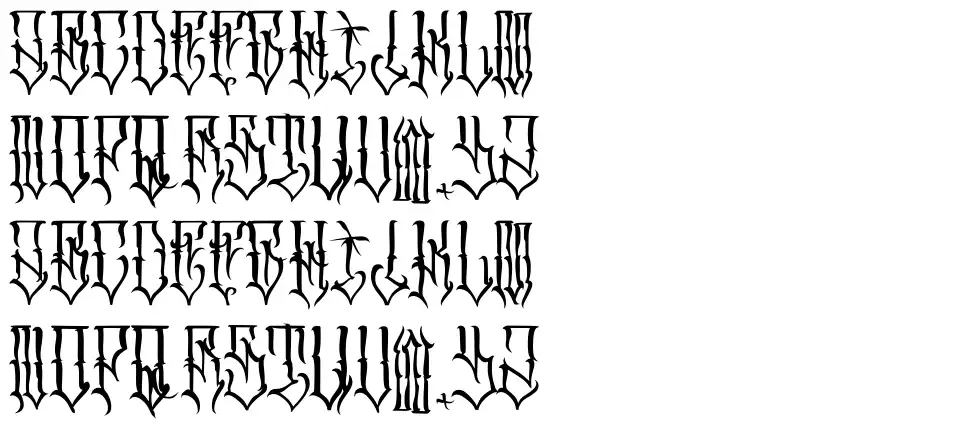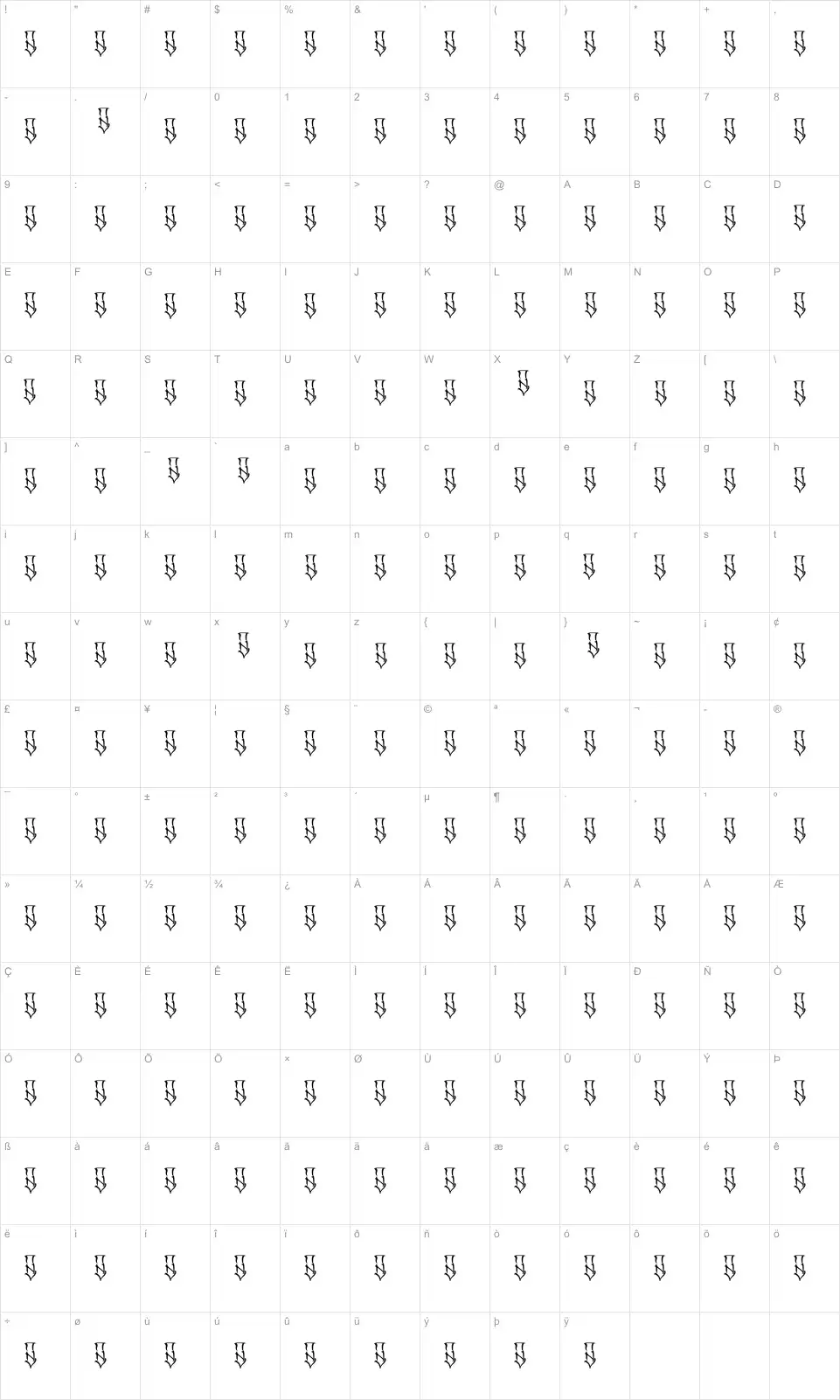
SR Cuen Font – Download Grátis
A fonte SR Cuen Font, criada pelo designer Cuen Medina, é uma escolha perfeita para aqueles que procuram um estilo de letra desenhado em graffiti. Suas linhas elegantes e expressivas oferecem uma maneira única de dar vida a qualquer texto ou logomarca. Licenciada sob a licença livre, a SR Cuen Font está disponível em formato TTF, permitindo que você personalize o texto ou faça preview online antes de usar. Esta fonte se encaixa perfeitamente na categoria de Script e Graffiti, adicionada em julho de 2022 e já foi baixada pelo menos 3548 vezes. Com um tamanho de 12 KB, ela é fácil de instalar e usar em qualquer projeto de design. Para mais informações e acesso ao designer, acesse o site: https://www.facebook.com/srcuen.